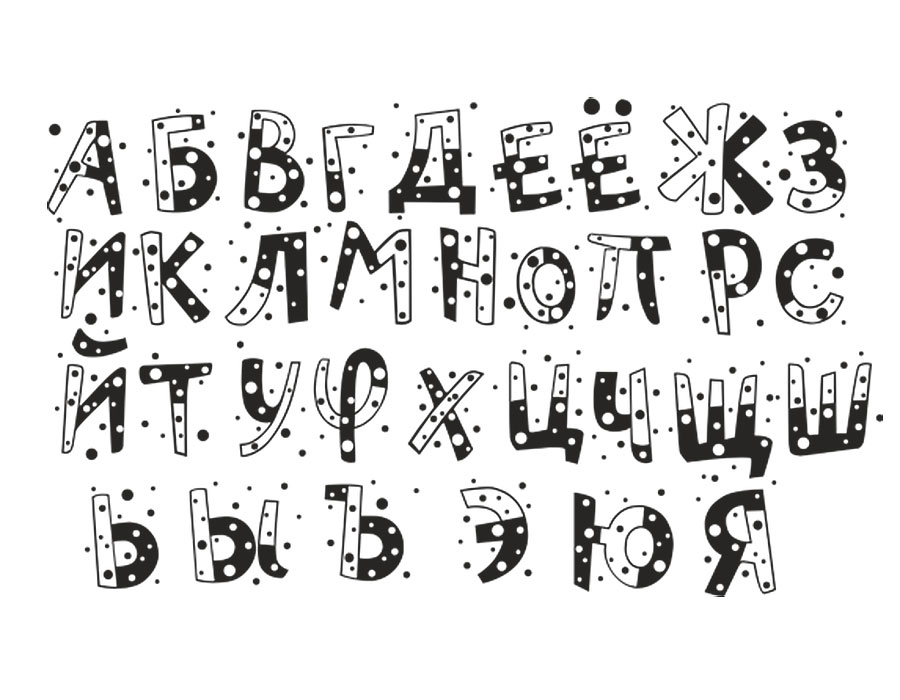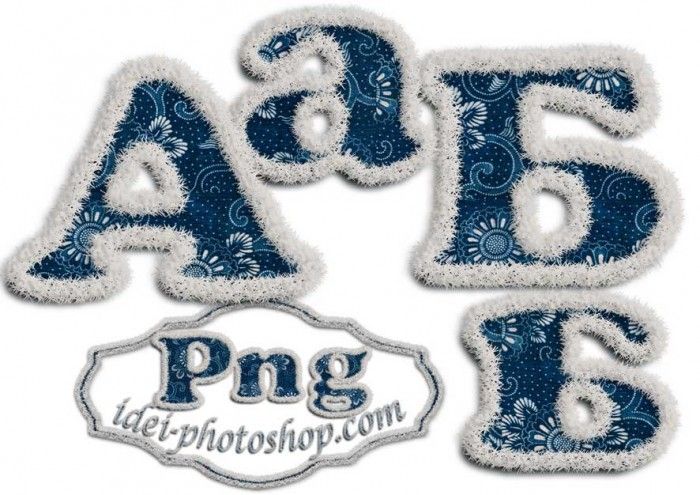
Новогодние шрифты и иконки для праздничного настроения (много кириллицы)
До Нового года осталось 10 дней – это ли не прекрасно? Сейчас самое время создавать новогоднее настроение себе и окружающим, в том числе и партнёрам, и клиентам, и коллегам. Очень здорово в этом может помочь подборка новогодних шрифтов и иконок.
Одно дело написать “С Новым годом” скучным Times New Roman, и совсем другое написать это же, но шрифтом Matterhorn (все буквы в снежных шапках). А кроме этого, есть ведь ещё множество новогодних и рождественских иконок – словом, инструментов для создания атмосферы уйма.
Так что без лишних слов – сразу к подборке!
Новогодние шрифты
1. Matterhorn
Matterhorn
2. Campanella
Campanella
3. Astakhov Access Degree AG
Astakhov Access Degree AG
4. Montresor
Montresor
5. Candy Cane
Candy Cane
6. Christmas Eve
Christmas Eve
7. Christmas Lights
Сhristmas lights
8.
DK Father Frost
09. Christmabet
Christmabet
10. Bodie MF Holly
Bodie MF Holly
11. Alfavita
Alfavita
12. HERMAN(RUS BY LYAJKA)
HERMAN(RUS BY LYAJKA)
13. Astakhov Dished ChAoS!
Astakhov Dished ChAoS!
14. Christmas/Flakes
Christmas/Flakes
15. PW Christmas
PW Christmas
16. Kingthings Willow font
Kingthings Willow font
17. Wonderland
Wonderland
18. Astakhov Dished Glamour
Astakhov Dished Glamour
19. Morning Glory and Cyrillic
Morning Glory and Cyrillic
20. Snowhouse
Snowhouse
21. One Starry Night
One Starry Night
22. DKClairDeLune
DKClairDeLune
23. a_MachinaNovaStarD Bold
a_MachinaNovaStarD Bold
24. a_BraggaStars
a_BraggaStars
25. Pudelinka
Pudelinka
26.
Kringle Regular
27. akaPotsley
akaPotsley
28. WindCTT
WindCTT
29. Whirl Cyrillic
Whirl Cyrillic
30. Hultog Snowdrift
Hultog Snowdrift